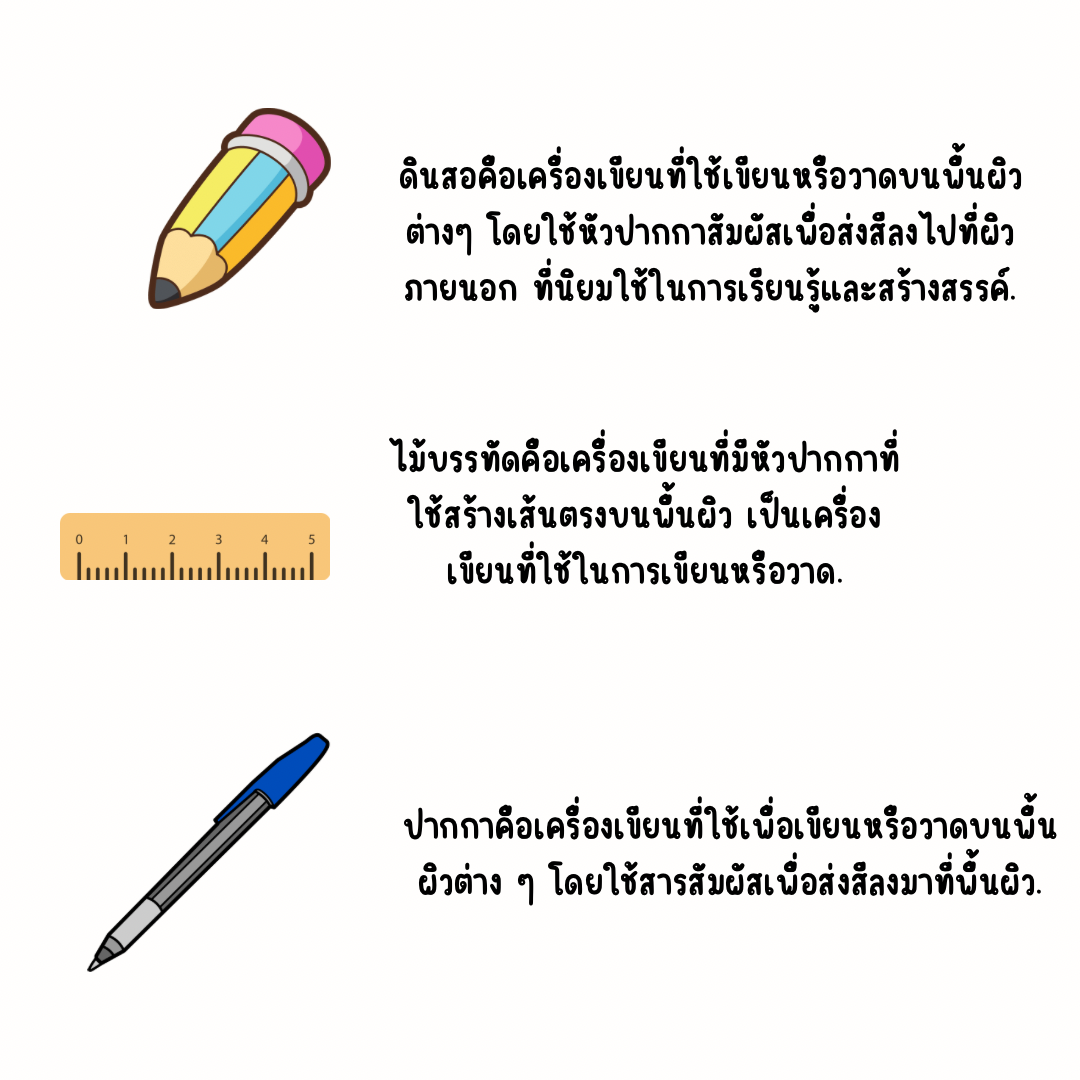
Momie
แจกฟรี!!!! ฟอนต์ลายมือ Momie
Momie เป็นฟอนต์ลายมือที่มีความมินิมอล ใช้แล้วสวย ใช้แล้วรวย ใช้แล้วดีเฮง ๆ ปัง ๆ รถ ๑๐ คัน บ้าน ๑๐ หลังต้องฟอนต์โมมี่ค่าาา เพี้ยงงง5555